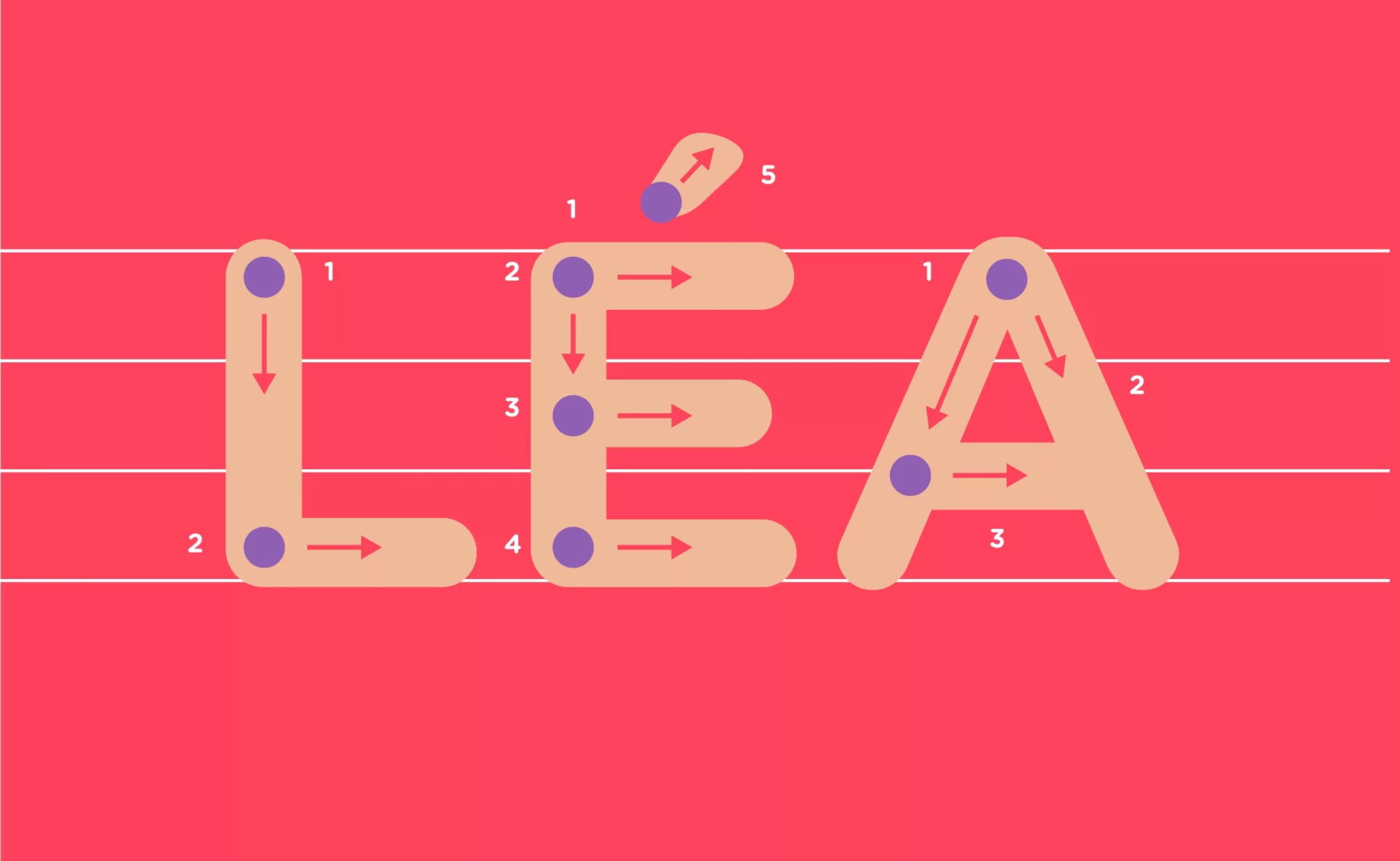
Anecdote de vacances…
Un dialogue de sourds entre un designer graphique et sa fille de 6 ans faisant son cahier de vacances…
La fille : “Papa, comment on écrit “les A” en majuscule ?”
Le père : “On fait un triangle avec une barre au centre.”
La fille : “Non !!! Comment t’écris “les A” en majuscule ?
Le père : “C’est un triangle avec un trait au milieu !”
La fille : “Non !!!! Mais je sais écrire les “A” !”
Le père : “Alors ? Tout va bien alors !”
La fille : ” Mais non !!!!! COMMENT ON ÉCRIT LES A EN MAJUSCULE !!!!”
Le père : “Regarde, je te montre avec les mains…”
La fille : ” MAIS NON…PAS C’EST COMME ÇA… T’ES NUL !!!!
COMMENT ON ÉCRIT LES A EN MAJUSCULE ???”
Le père : “Euh… déjà on baisse le ton… et ensuite, je suis graphiste, je sais écrire un “A” !!!”
[…] La fille : ” Pfff !!!!! mais c’est “LÉA“, comme la petite sœur d’Anaïs !!!”
Le père : [ Fou rire ]